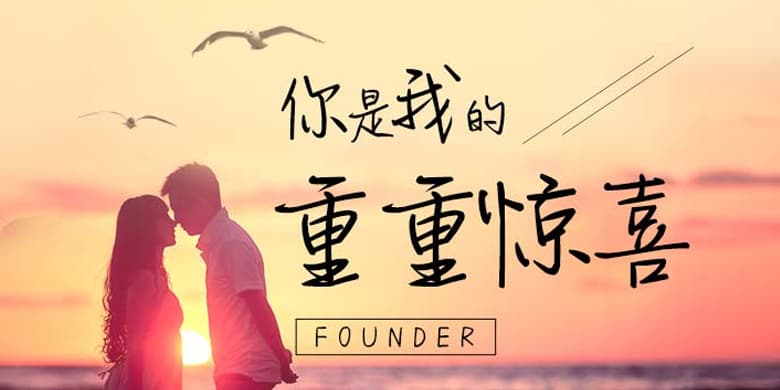
品牌:方正手迹设计师:尚正中发行时间:2020字库编码:大陆简体(GB2312-80)分类:常规书写·硬笔字体属性:精品字
这款字体几乎没有使用到连笔,行笔注重抑扬顿挫,及其富有韵律感。中宫较为紧凑,外围舒展,整体有强烈的节奏感和速度感。适用于文艺类的书刊、品牌广告和产品包装设计,以及社交网络的个性化用字。